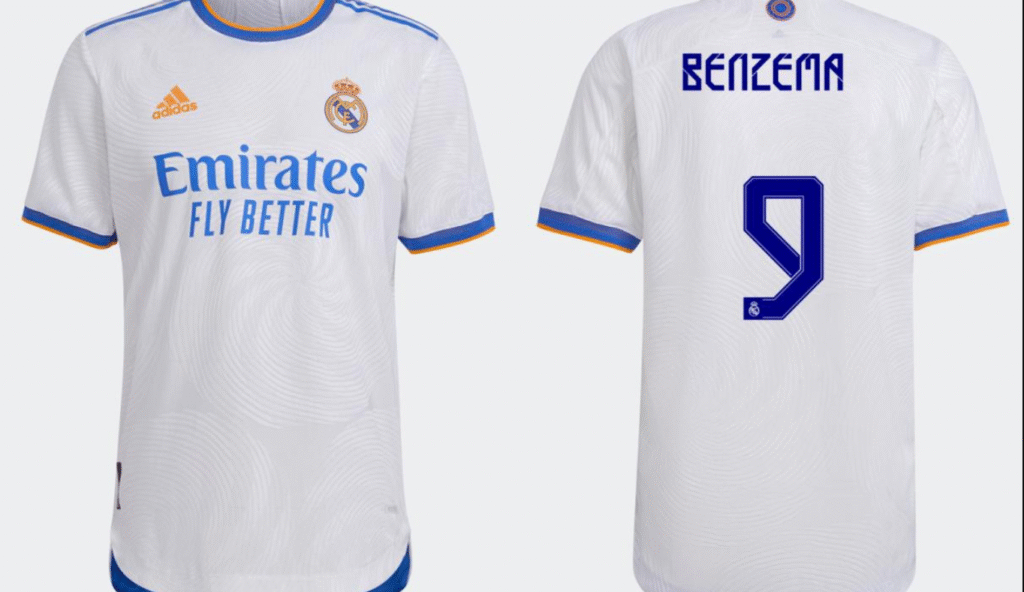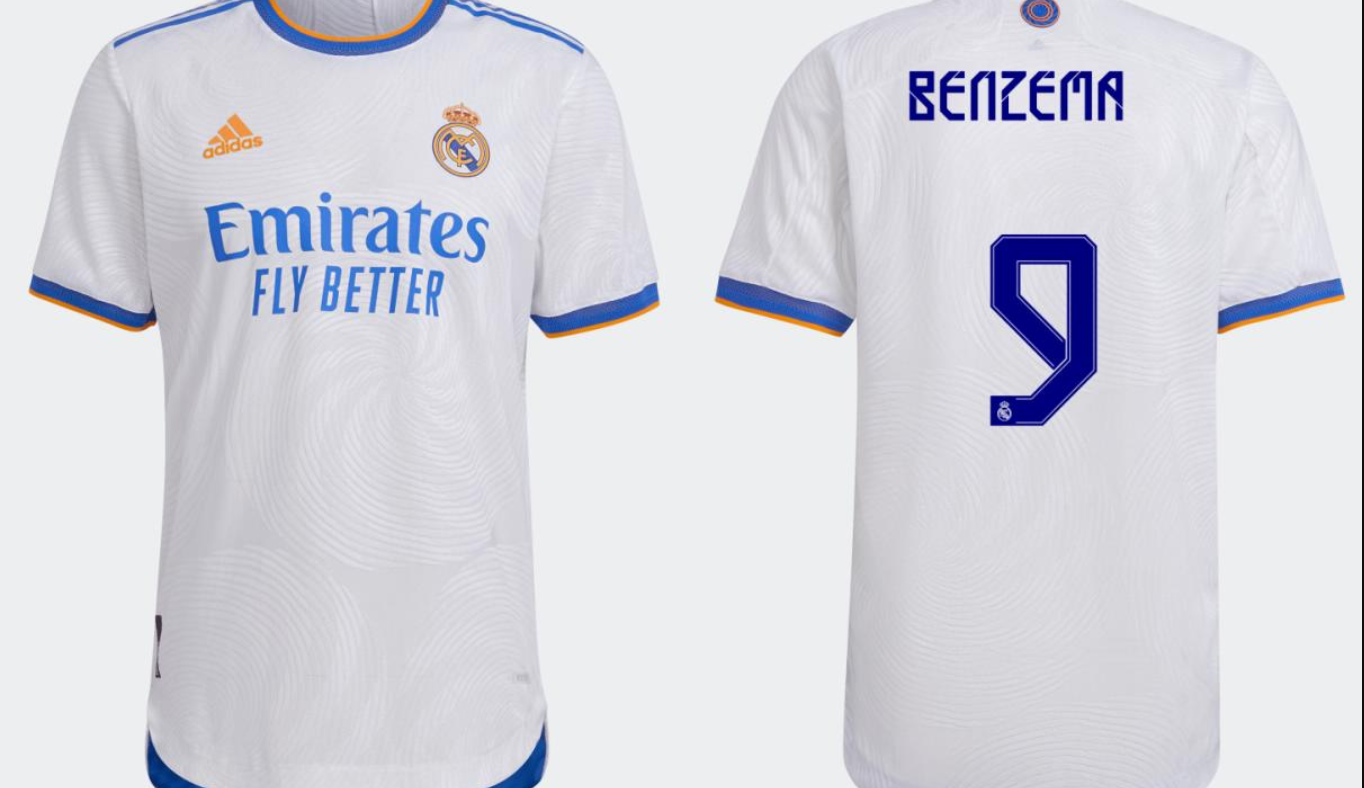
Se existe uma camisa que pesa, é a do Real Madrid. E a temporada 2021-2022 entrou para a história como uma das mais emocionantes, culminando na conquista da “La Decimocuarta” (a 14ª Champions League).
Para designers e personalizadores, ter acesso à tipografia exata usada por lendas como Karim Benzema, Luka Modrić e Vinícius Jr. é fundamental para recriar a magia daquele ano. Neste post, trazemos a fonte oficial utilizada pela Adidas nas competições europeias e na Copa do Rei (diferente da fonte genérica usada na La Liga), pronta para seus projetos.
- Conteúdo: Alfabeto completo e numeração oficial com o detalhe interno (linhas).
Estilo Visual: Inspiração em Cibeles
A tipografia criada pela Adidas para esta temporada é uma verdadeira obra de arte conceitual. Ela foi inspirada na icônica Plaza de Cibeles, o local sagrado onde a torcida Merengue celebra seus títulos em Madrid.
O design se destaca pelas linhas concêntricas e curvas em espiral dentro dos números e letras, simulando a arquitetura e a energia da fonte da praça. É uma fonte moderna, artística e que foge completamente do padrão bloco sólido, trazendo um visual de movimento e elegância para o uniforme branco e para o kit azul (visitante).